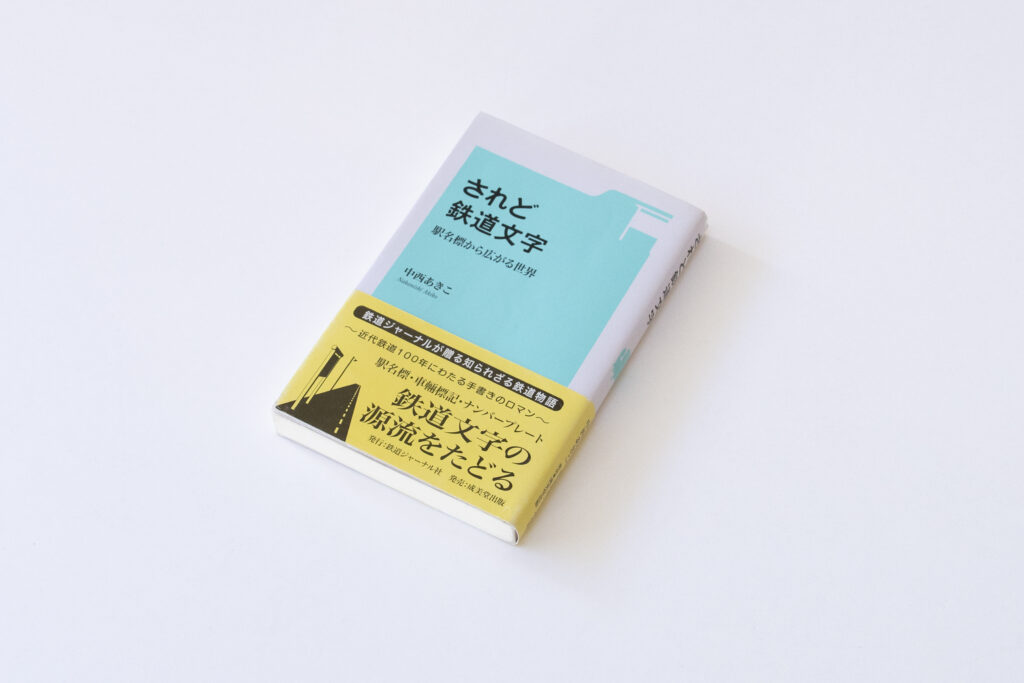
TPの書庫から『されど鉄道文字』
今回は、中西あきこ著の『されど鉄道文字 駅名標から広がる世界』をご紹介します。
日ごろ電車を利用する中で欠かせない案内や駅名の表示に使用されている書体が、どのようにして選ばれたのか気になりました。タイププロジェクトのAXIS Fontも西武鉄道のサインシステムに使用されており、本書で言及されている鉄道で使われてきた旧い文字から現在までのつながりに興味を持ち選書しました。
職人による手書きから始まった国鉄の駅名標に使われた書体の「すみ丸ゴシック」。本書は当時を知る関係者やエピソードにあたって書体がどのようにして書かれその形になったのか、鉄道文字の現在までの変遷を丁寧に辿っています。
人々が鉄道を快適に利用するために、職人それぞれが腕を揮って文字を書いたことや、それを整備して鉄道をとりまく状況や時代の変化に合わせて永らえるために守ってきた人の「良くしていこう」という姿勢が伝わってきます。魅力的な鉄道文字から、長く愛され使われ続ける文字について考えられる一冊です。
続いて『されど鉄道文字』に関連して弊社の鈴木から選書へのコメントです。
終章にある中西さんの指摘「一つの書体が長らえるヒント、それはおそらくリデザインにある」は、私も同感。都市フォントのお手本的存在と考えてきたロンドンの地下鉄書体ジョンストン・サンズが例にあがったくだりでは思わず手を打ちました。鉄道書体とリデザインを主題として掘り下げたい人には『ジョンストンのロンドン地下鉄書体』がおすすめ。継続性の観点がますます重要になってきた昨今『されど鉄道文字』と合わせてどうぞ。
『されど鉄道文字 駅名標から広がる世界』
『ジョンストンのロンドン地下鉄書体』